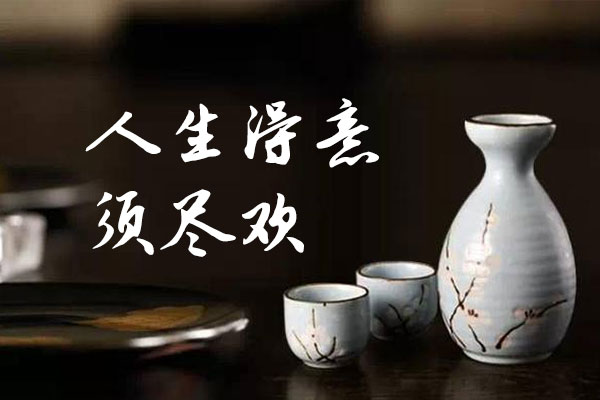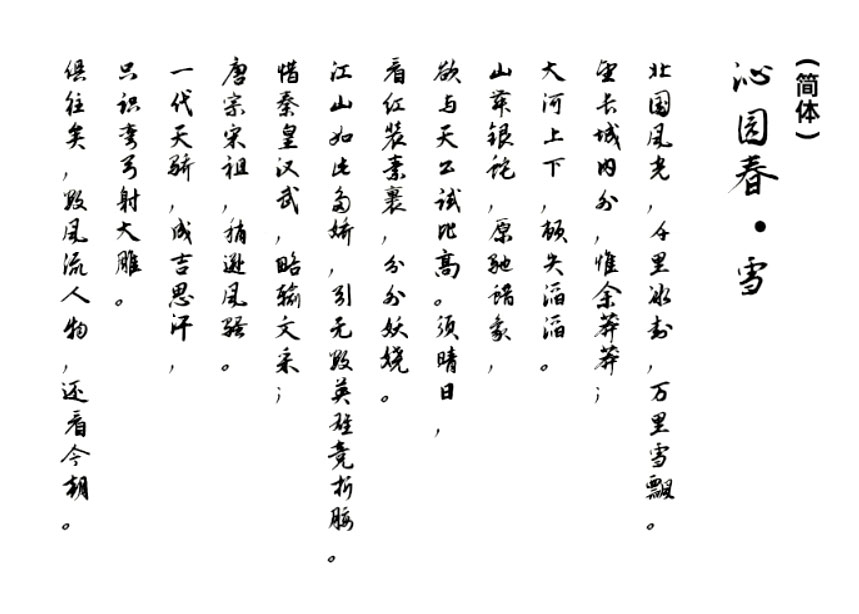
钟齐志莽行书
钟齐志莽行书是一种行书字体,它的设计风格独特,笔触自然流畅,富有动感。该字体适用于各种设计场景,无论是海报设计、品牌形象设计还是包装设计等,都能为您的作品增添一份独特的韵味。
此外,谷歌开源字体项目还提供了钟齐志莽行书的多种语言支持,以及完善的Unicode字符集覆盖,以确保您的文本在不同的显示设备和操作系统中都能够得到一致的呈现效果。
总的来说,钟齐志莽行书是一种极具实用价值的字体,您无需任何费用即可使用它来为自己的设计增添独特的魅力。